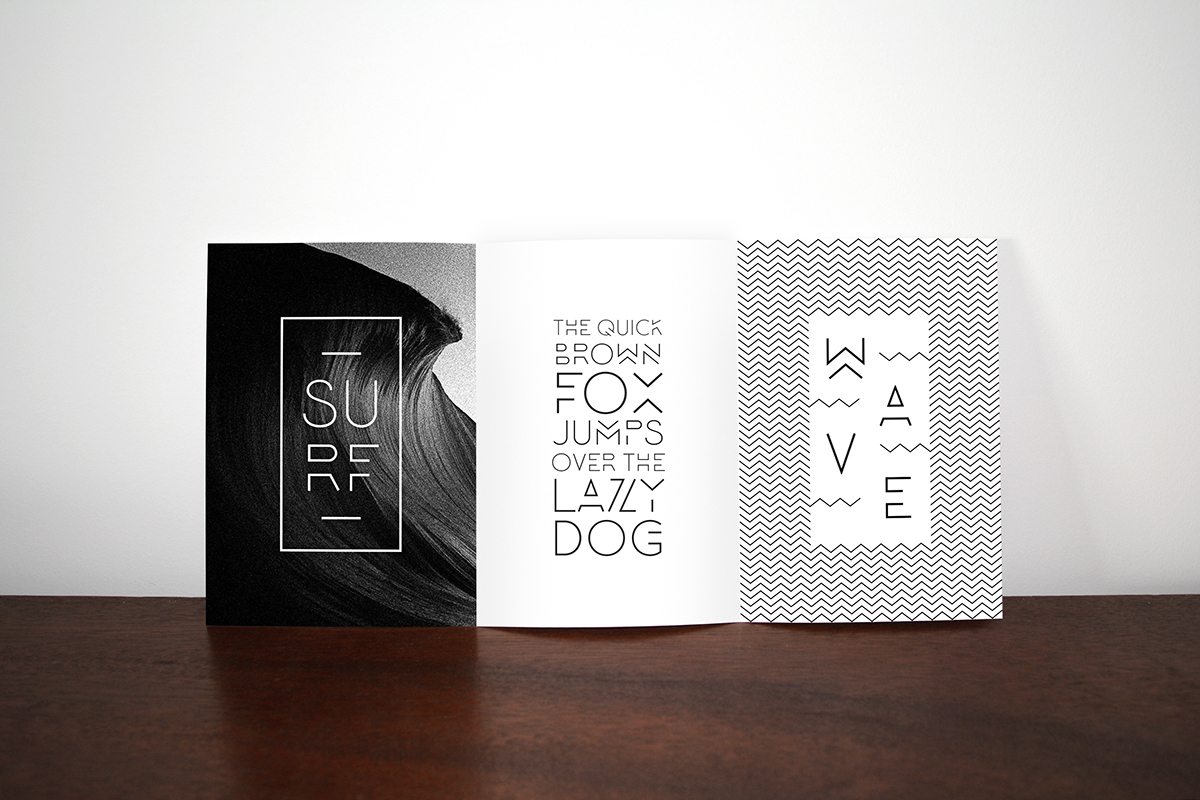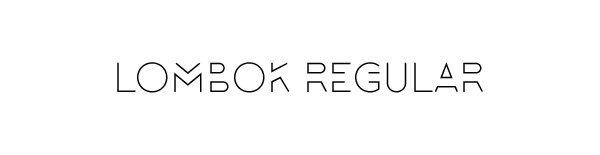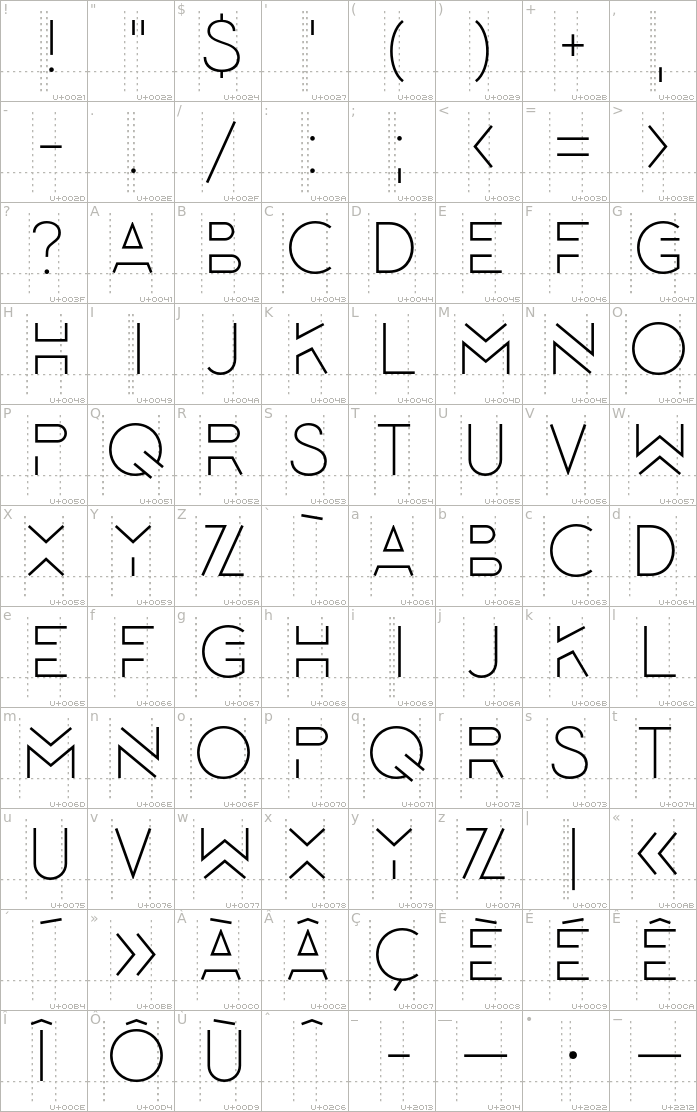
Font del giorno: Lombok Regular
Se siete alla ricerca di un font che sia ben  caratterizzato, con una fortissima personalità, ma che mantenga comunque un’alta leggibilità, allora avete trovato ciò che cercavate.
Il font lombok creato dallo studente svizzero, Alexandre Pietra è davvero eccezionale: rispettando tutte le caratteristiche regole dello stile helvetico, è riuscito a creare un font elegante con un movimento eccezionale e molto caratteristico.
Ideale per creare dei loghi o delle intestazioni eleganti.